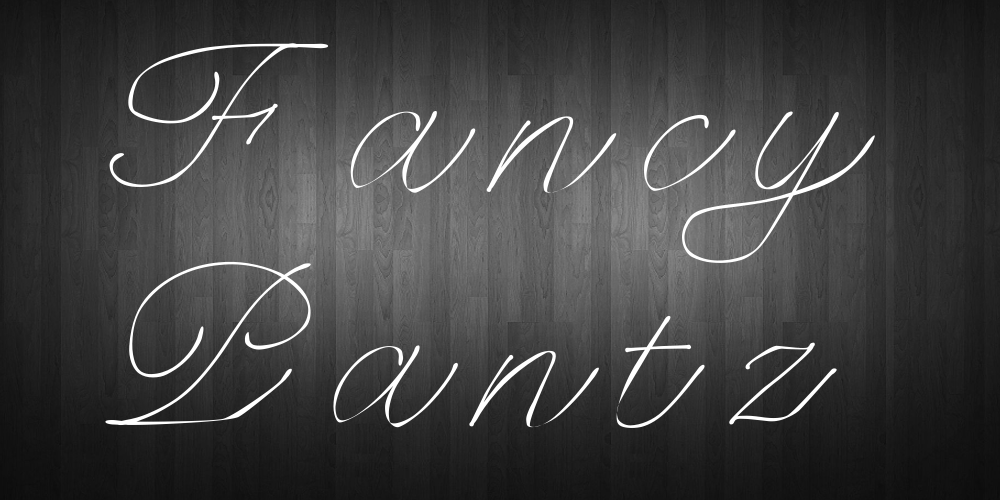
Fancy Pantz Font
Aqui está uma descrição para a página de download da fonte ‘Fancy Pantz Font’, com foco no seu estilo script: ‘Veçada em um design elegante e fluido, a Fancy Pantz é perfeita para aqueles que desejam adicionar um toque sofisticado às suas criações. As linhas arredondadas e curveiras leves conferem ao texto um aspecto vibrante e fresco. Os detalhes emoldurados criam uma sensação de elegância, tornando a Fancy Pantz uma escolha ideal para projetos pessoais ou comerciais. Feita pelo talentoso designer Hamilton, esta fonte é licenciada gratuitamente para uso pessoal, oferecendo-lhe flexibilidade ao criar. Para mais detalhes e acesso à esta fantástica fonte de script, acesse o site da Digigardin.com. Combinar essa fonte com outros elementos design pode transformá-lo em uma peça única e impactante.’ Esta descrição mantém os tópicos originais mas adiciona um tom mais informacional e convidativo, sem incluir nomes ou características inexistentes na descrição original da font.